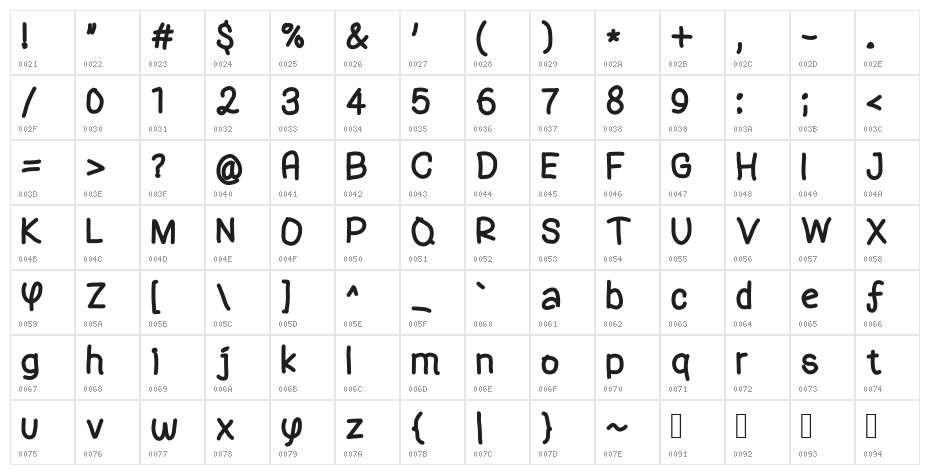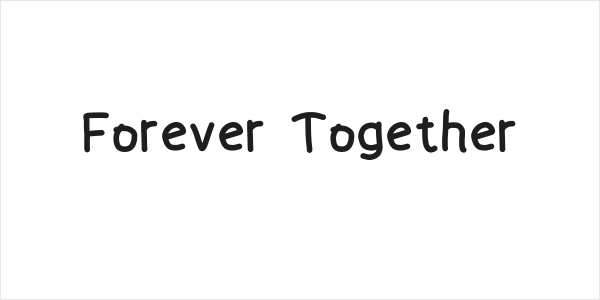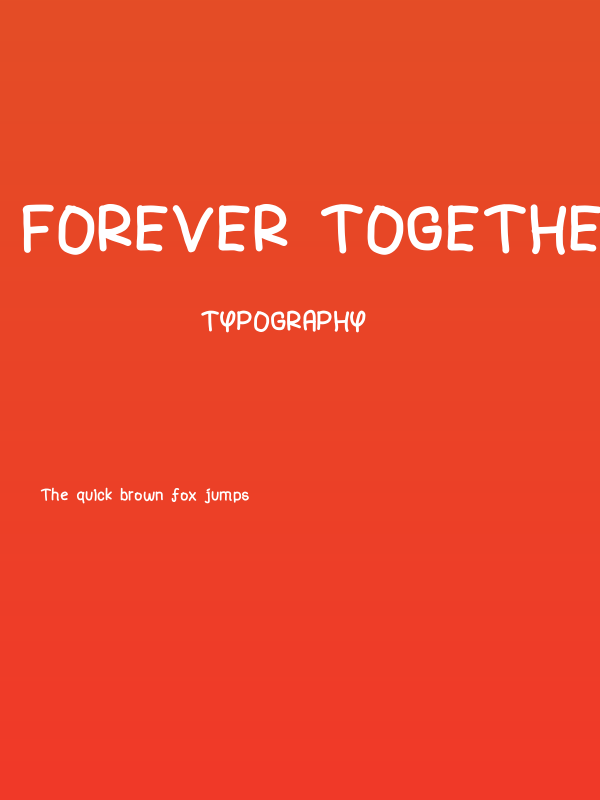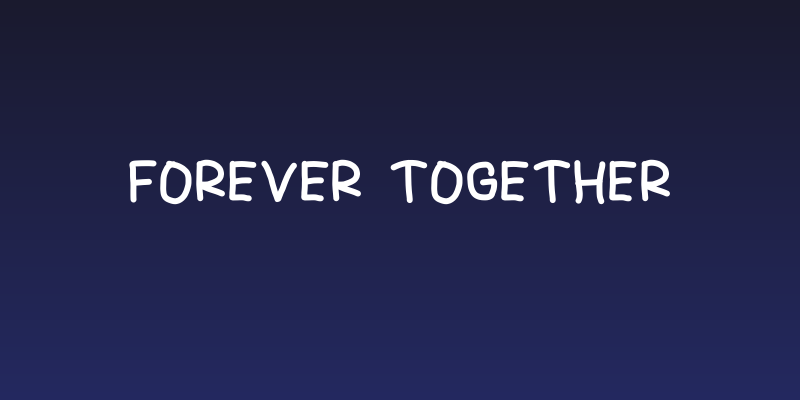
Forever Together Font
| 全体的なスタイル | Casual |
| 用途 | Headlines, Logos, Informal Text |
| おすすめプロジェクト | Ideal for children's books, greeting cards, playful branding, and casual invitations. |